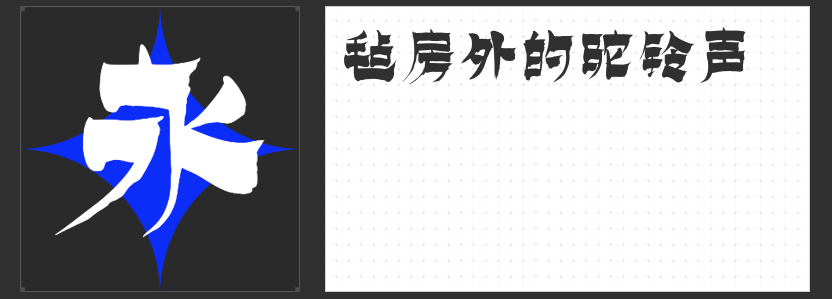
新中式字体推荐:四款造字侠与云书法力作
在字体设计的浩瀚宇宙中,新中式字体以其独特的韵味和深厚的文化底蕴,成为了设计界的宠儿。今天,就让我们一起走进四款新中式字体的世界,感受它们带来的视觉盛宴。
首先推荐的是“造字侠永刚漆书简繁”。这款字体如同一幅生动的毛笔手书,笔画厚重而不失灵动,撇字清晰从容,展现出极高的艺术性。框架醒目,字型端庄,字体风格统一,使得它在包装印刷、广告设计、平面设计等领域中脱颖而出。无论是商业宣传还是文化展示,都能完美诠释新中式风格的精髓。
接下来是“造字侠磅礴简繁”。这款字体中正感官丰富,运笔富有节奏感,仿佛能让人听到笔画间流转的旋律。一波三折的笔画形态,粗细变化明显的线条,以及略带飞白的转折,都使得这款字体充满了生命力和动感。方圆结合的转折处理,更是为其增添了几分大气与豪迈。
“云书法玉兰行楷体”则是一款气韵生动、刚柔并济的毛笔字体。整体字形匀称美观,主笔画凸出,块面感明确,层次感丰富。运笔自然流畅,笔画灵动洒脱,韵律感十足,仿佛能让人感受到书写者的情感与呼吸。笔画间的牵丝连带,书写具有连贯性,使得这款字体在海报、文创、书籍封面、影视娱乐等多种应用场景中都能大放异彩。
最后要介绍的是“造字侠仗剑简繁 传神”。这款字体字形稳重而不失张扬,笔画间透露出一种豪侠之气。折、提、钩等部首干净利落、高度折叠,颇有豪侠仗剑江湖的潇洒之感。传神之处在于其笔画间的力度和速度感,仿佛能让人看到书写者挥毫泼墨的英姿。
这四款新中式字体各具特色,无论你是设计师还是书法爱好者,都能在其中找到心仪的选择。它们不仅代表了新中式字体的高水平创作,更是中华文化传承与创新的重要载体。让我们一同品味这些字体带来的美感与韵味吧!